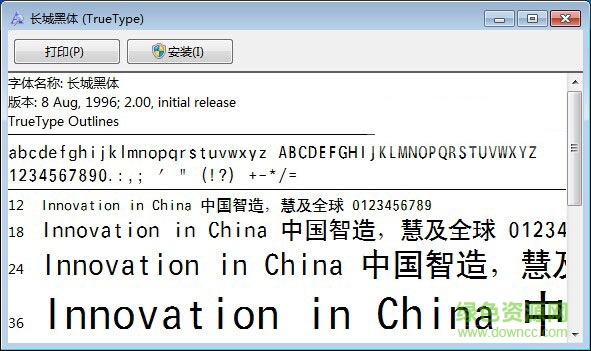
ghei01m是什么字體?Ghei01m字體就是長城黑體字體,筆畫粗細(xì)勻稱,無裝飾無弧線,閱讀清晰,辨識(shí)度強(qiáng),應(yīng)用范圍廣泛!
黑體字又稱方體或等線體,是一種字面呈正方形的粗壯字體,字形端莊,筆畫橫平豎直,筆跡全部一樣粗細(xì),結(jié)構(gòu)醒目嚴(yán)密。黑體適用于標(biāo)題或需要引起注意的醒目按語或批注,因?yàn)樽煮w過于粗壯,所以不適用于排印正文部分。
橫平豎直字見方 ,大小粗細(xì)一個(gè)樣 ,上緊下松要記牢 ,筆畫穿插又避讓 ,自隙均勻要講究 ,整齊美觀又大方